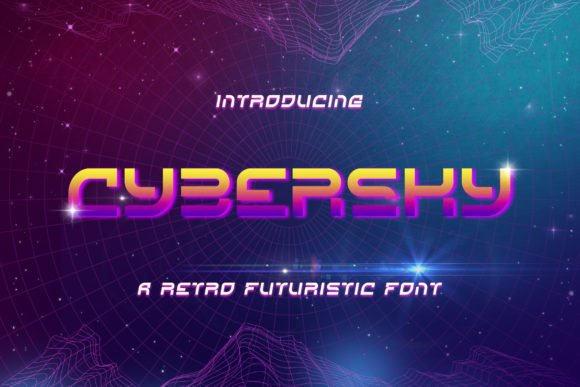
Creativefabrica Cybersky Font 2021
[Creativefabrica] Cybersky Font (2021)
Cybersky - это резкий, угловатый и футуристический шрифт, выполненный в стиле ретро.
Он будет потрясающе смотреться на любом плакате, листовке или печати.
Используйте этот шрифт для своих проектов и исследуйте его безграничные возможности.